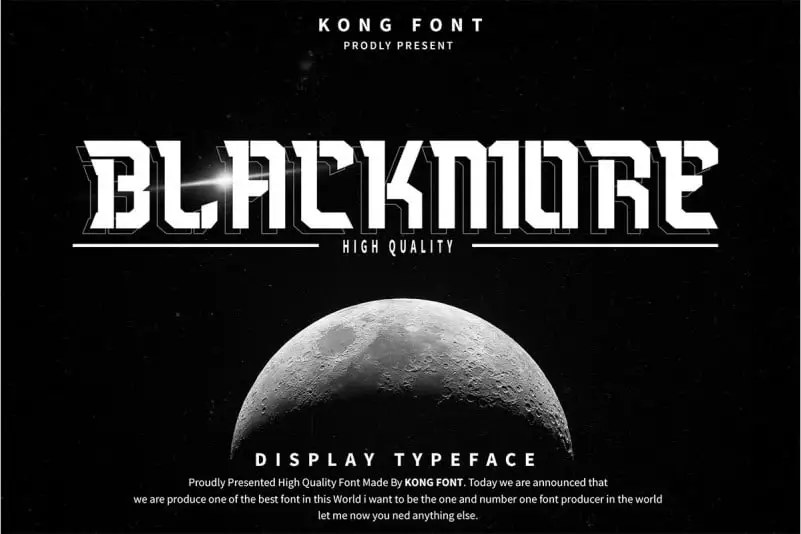
Blackmore Display Font – Download Grátis
A Blackmore Display Font é uma tipografia sans-serif geométrica que traz estilo elegante para projetos visuais criativos. Ideal para aplicar em identidades digitais, logotipos e páginas de landing com um toque moderno e minimalista, ela oferece a opção perfeita de se destacar no mercado digital contemporâneo. Seu design geométrico leva à uma aparência firme e clean que se adapta a qualquer projeto visual exigente, tornando-a uma escolha ideal para quem busca unidade de estilo e sofisticação em suas criações visuais. Com sua estética única, ela irá transformar qualquer projeto em algo realmente especial. Em contraste com outros tamanhos de fontes, a Blackmore Display é perfeita para textos grandes e visíveis, garantindo que seu design brilhe na tela. Este é o tipo certo para quem busca uma combinação única de sofisticação e clareza no seu projeto visual.